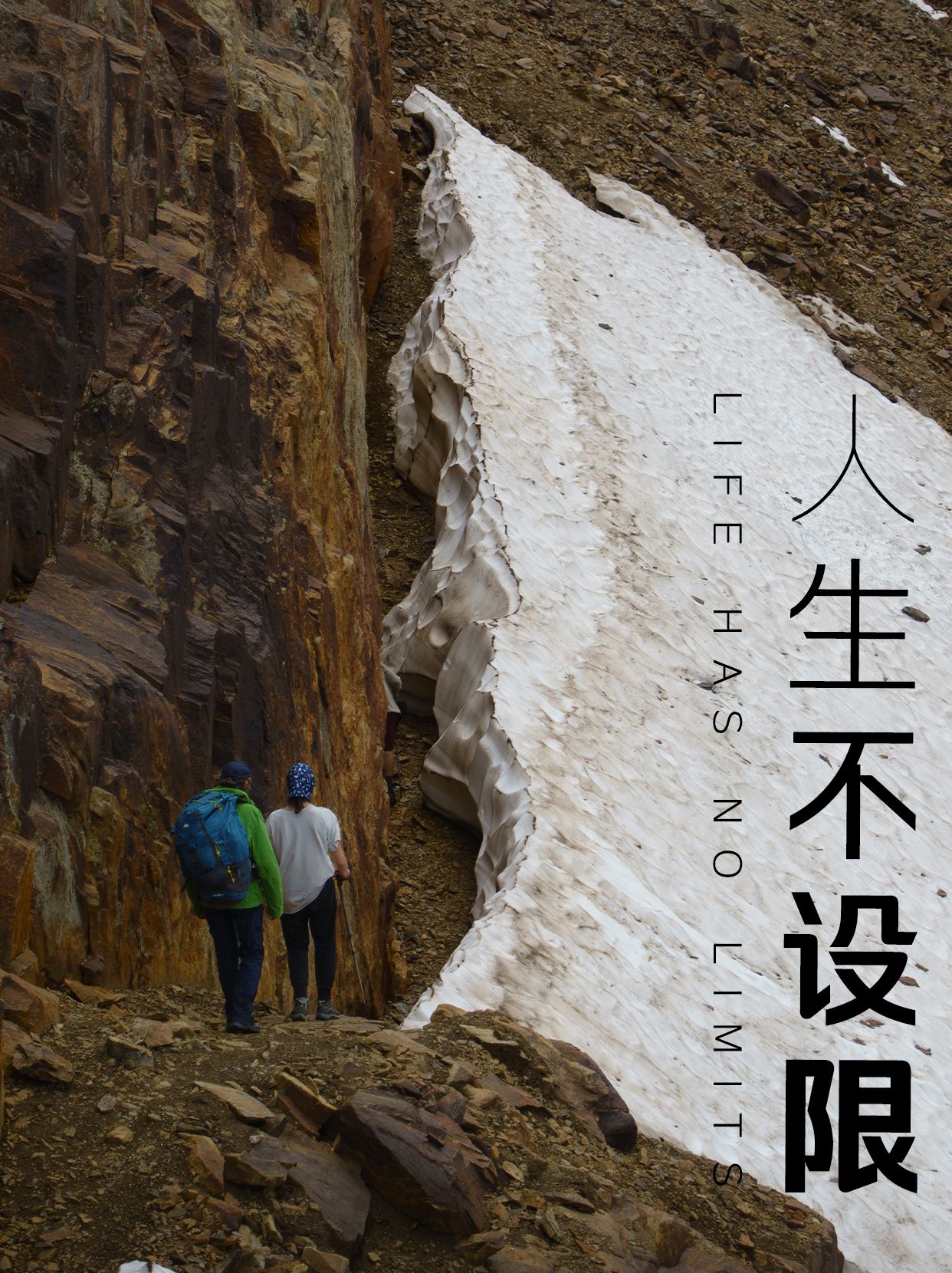
【字体推荐】四款内嵌字体,让设计更出彩
在设计领域中,选择合适的字体对于提升作品的整体质感至关重要。无论是制作PPT、海报还是网页设计,字体都是不可忽视的一环。今天,我将为大家推荐四款适合用于内嵌的字体。这四款字体各具特色,适用于不同的设计场合。
1.励字志向黑简 超粗
“励字志向黑简 超粗”是一款极具力量感的字体。其超粗的笔画给人以强烈的视觉冲击力,非常适合用于强调重点信息,如标题、标语或是宣传语。该字体的粗犷风格能够迅速吸引观众的目光,让人一眼就能捕捉到核心内容。它适用于那些需要展现决心和力量的设计项目,比如体育赛事海报、品牌广告等。
2.励字超级勇士简 特细
与上述字体形成鲜明对比的是“励字超级勇士简 特细”。这款字体线条纤细,透露出一种轻盈、优雅的气息。特细的笔触赋予文字一种飘逸之感,适合用于正文排版,特别是在需要大量文字的情况下,能够保证良好的阅读体验。如果你正在寻找一款既能体现细腻情感又能保持清晰度的字体,那么“励字超级勇士简 特细”将是不错的选择。
3.励字仿宋简繁
作为一款经典的宋体字体,“励字仿宋简繁”保留了传统宋体的韵味,同时又进行了现代化的改良。它既适用于中文简体也适用于繁体环境,广泛应用于正式文档、书籍出版以及学术报告中。这种字体的字形端正、结构清晰,不仅美观大方,而且易于阅读,是正式场合下不可或缺的好帮手。
4.励字书宋简繁
最后要介绍的是“励字书宋简繁”。这款字体在保持宋体基本特征的基础上,增加了更多的书写感,使得每个字符都显得更加灵动自然。它既适用于正式文件,也能很好地适应一些创意性的设计需求,如书籍封面、杂志排版等。其独特的笔触变化为文字增添了一份艺术气息,能够帮助设计师们创造出既有文化底蕴又不失现代感的作品。
总而言之,这四款字体各有千秋,可以根据具体的设计需求来灵活选择使用。无论是追求力量感、轻盈感、正式感还是艺术感,总有一款适合你的设计项目。希望今天的推荐能为你的设计工作带来新的灵感!